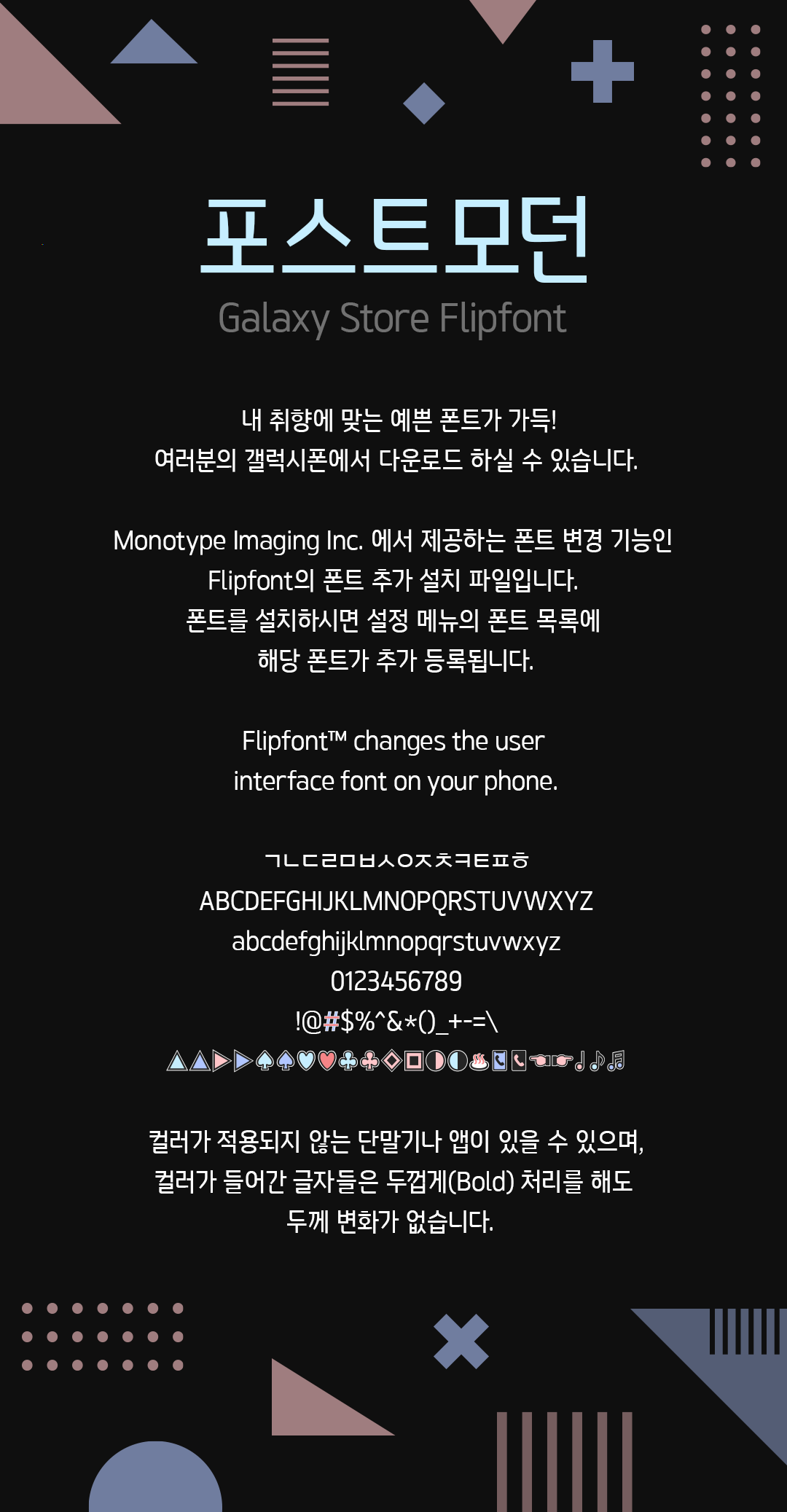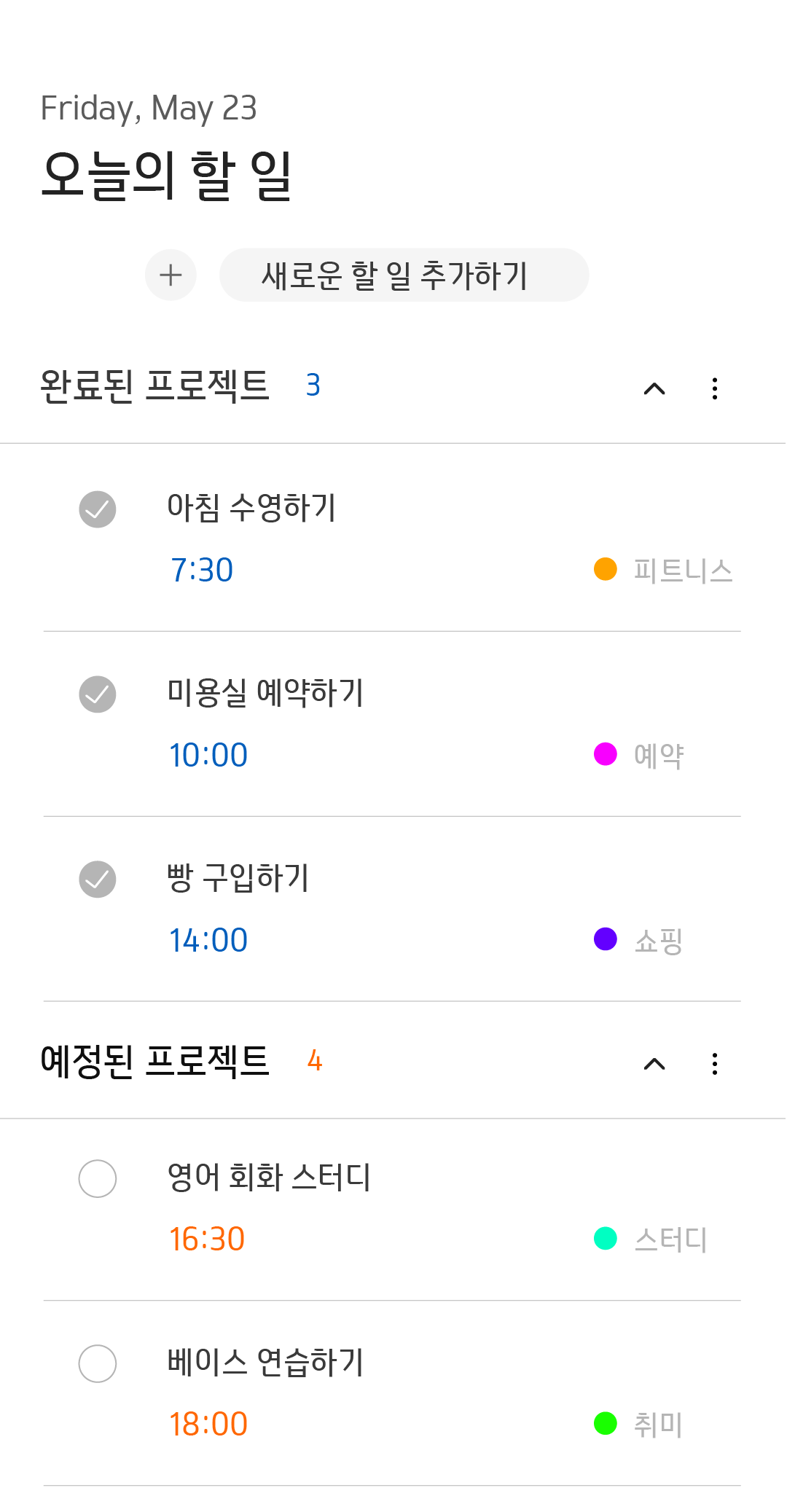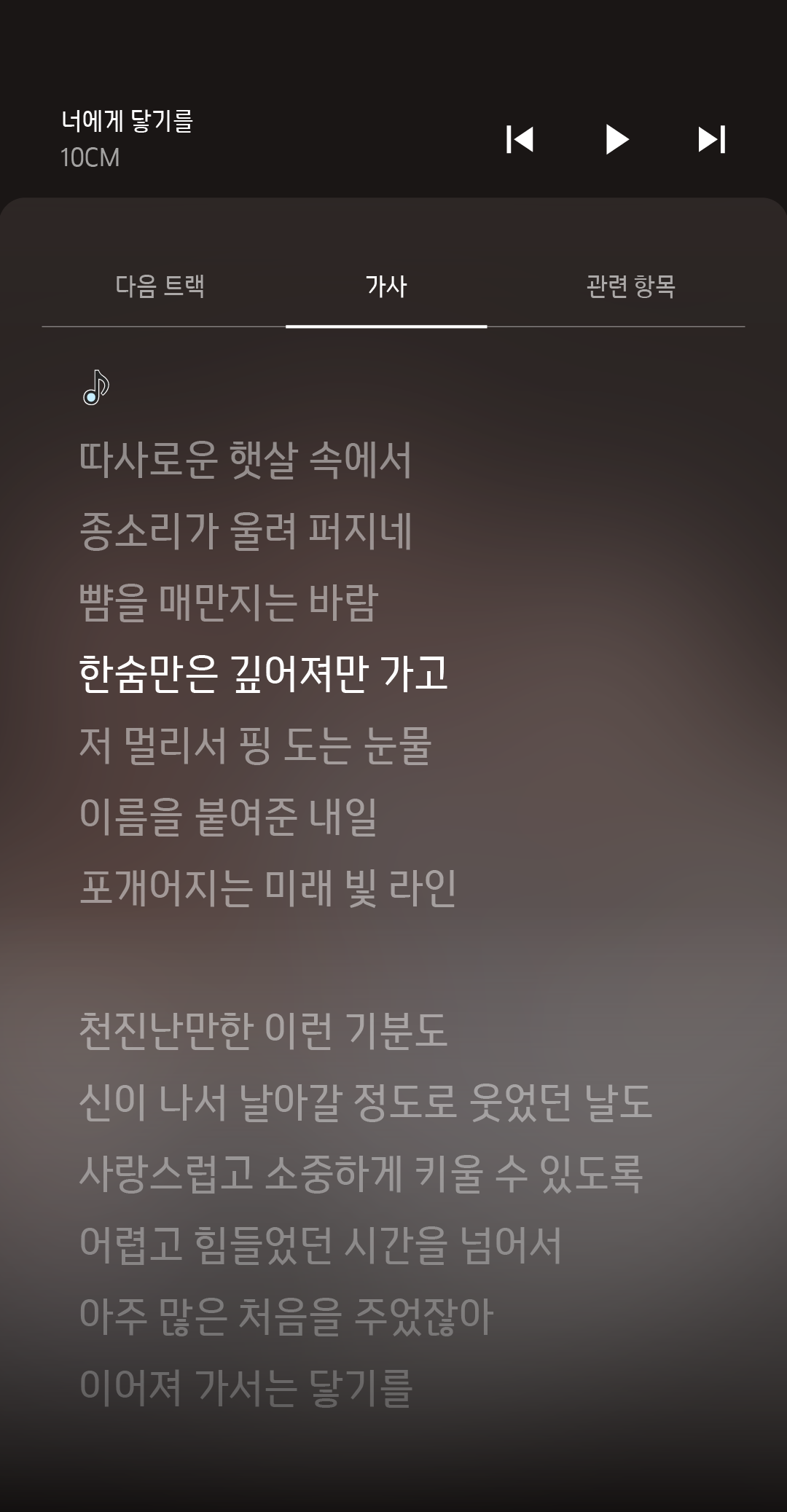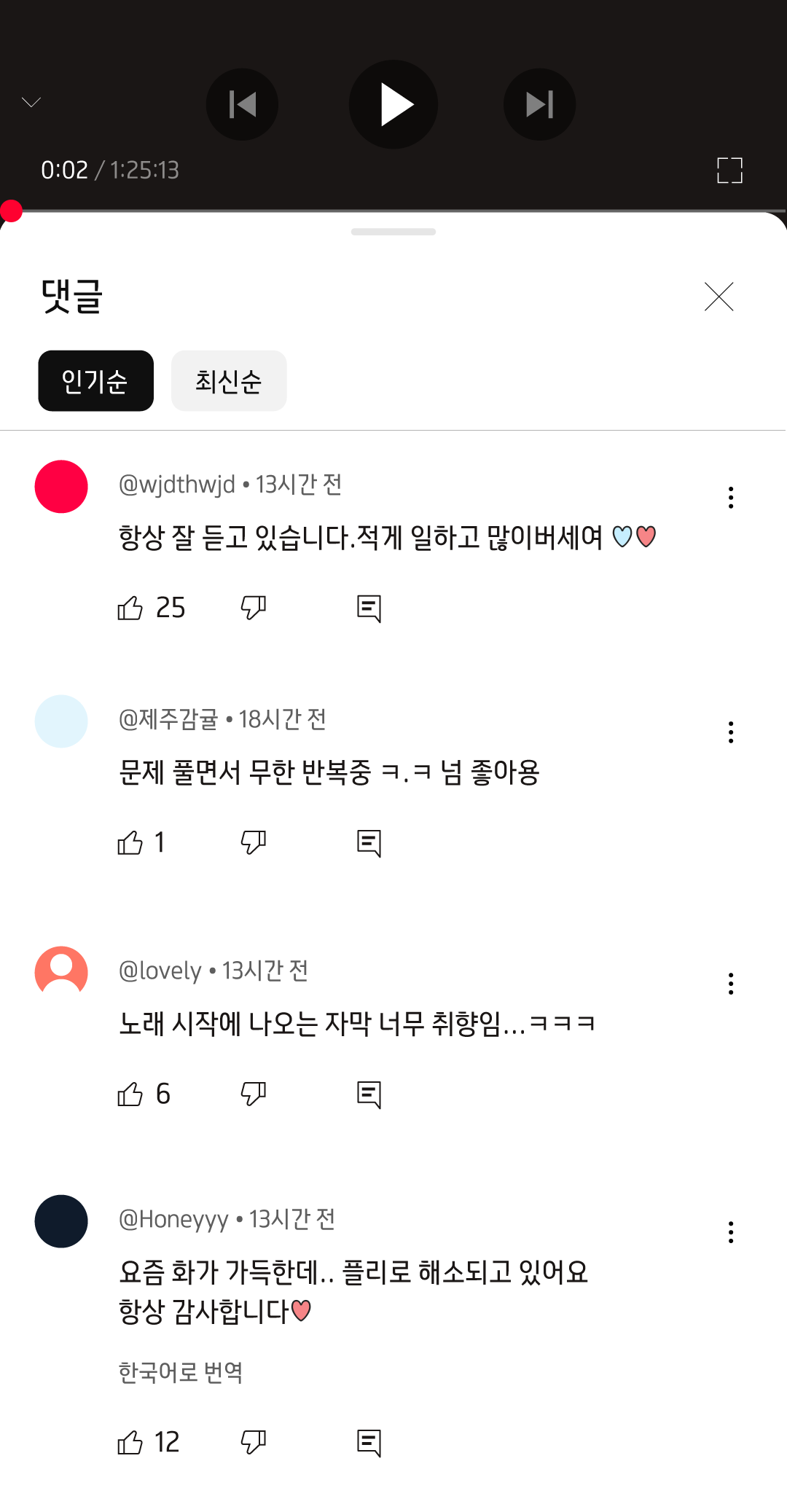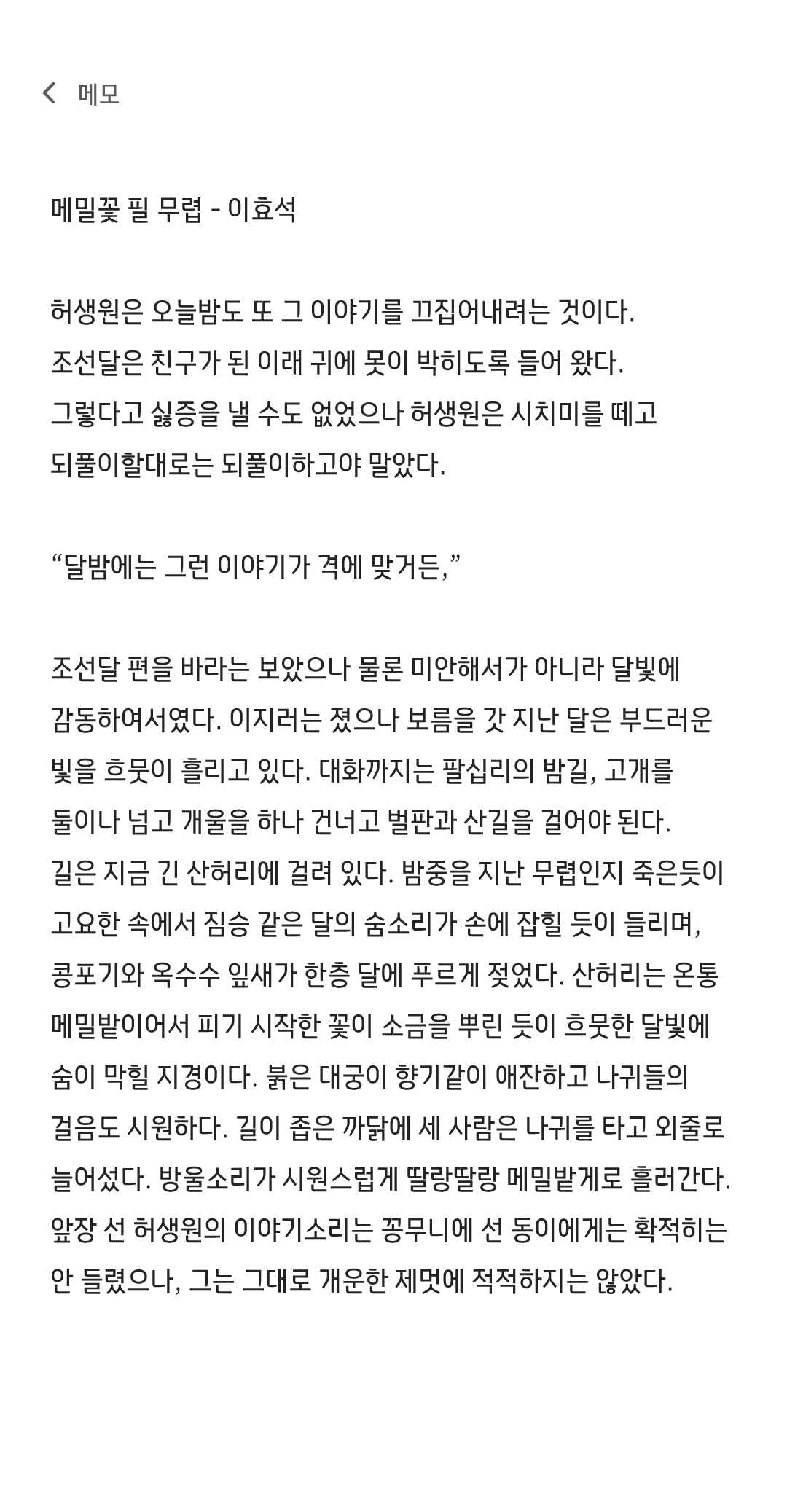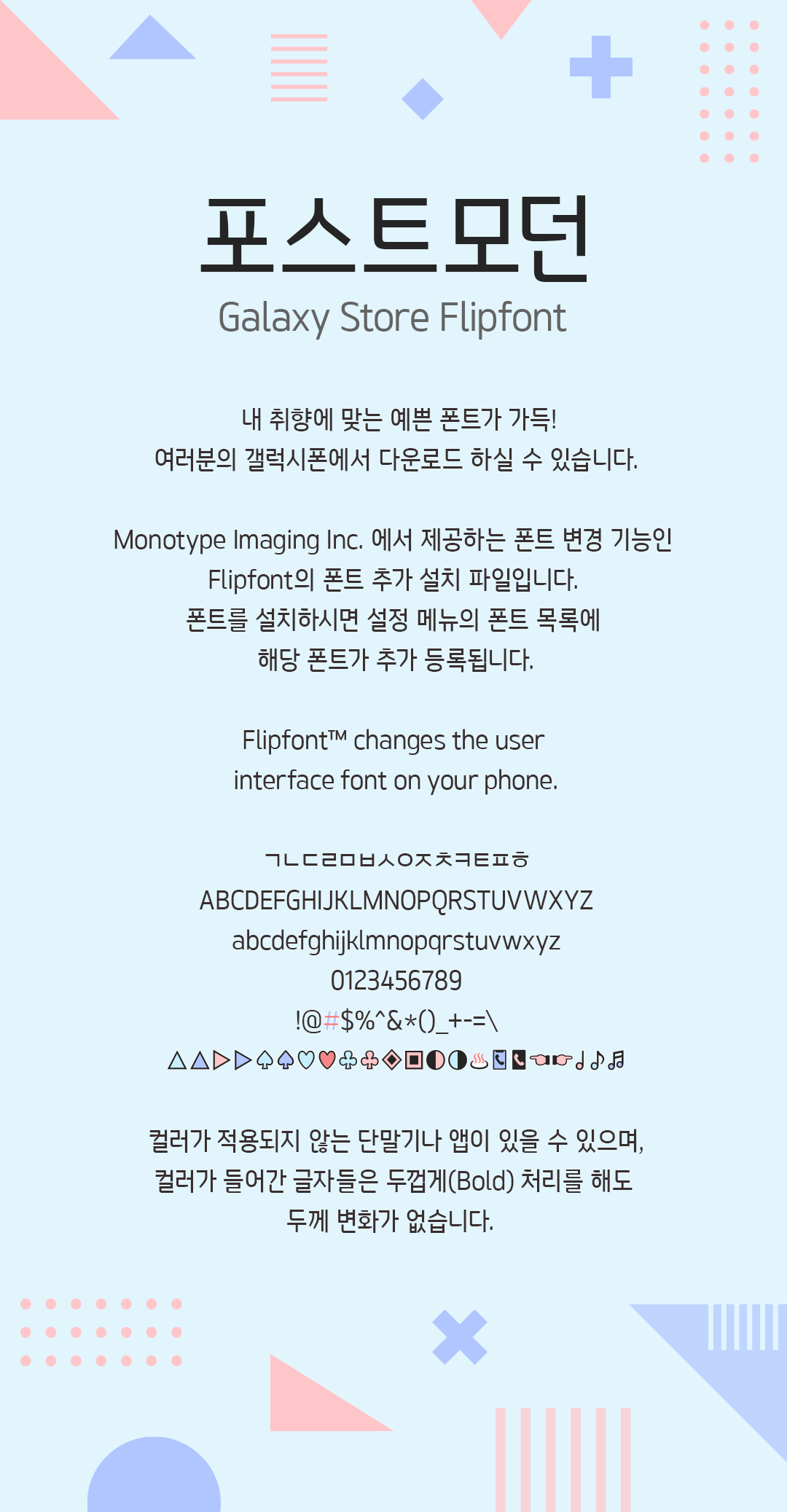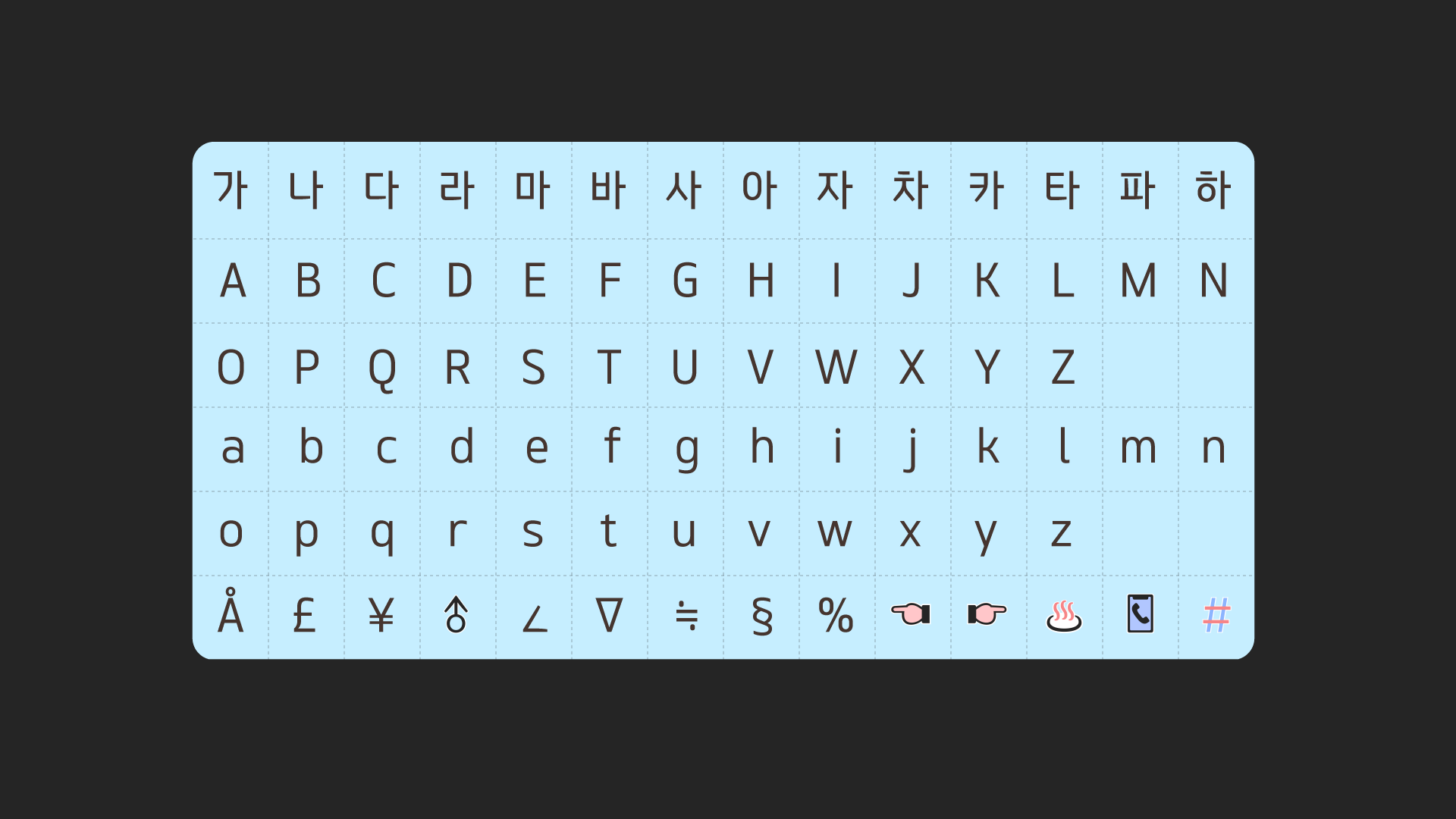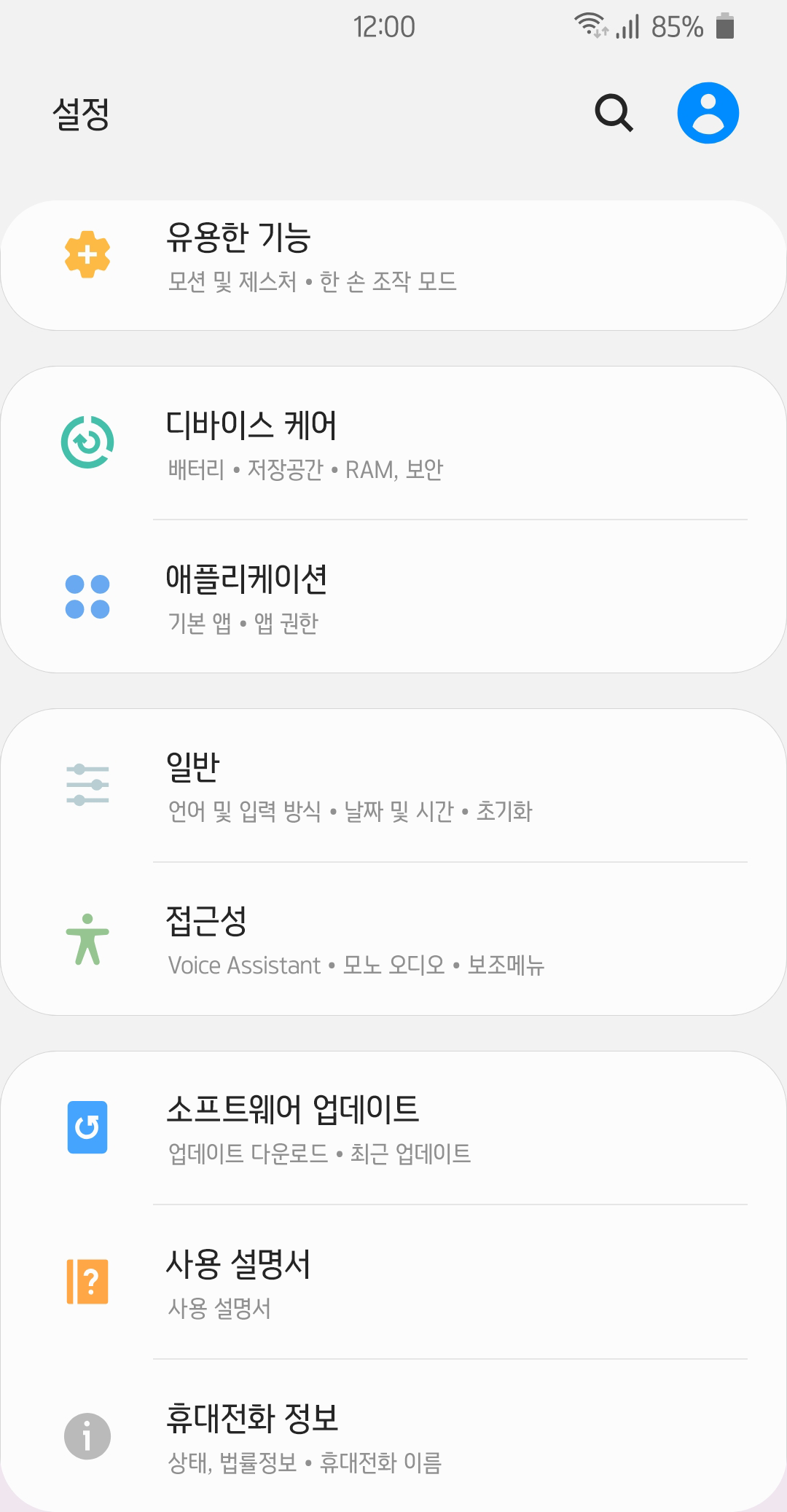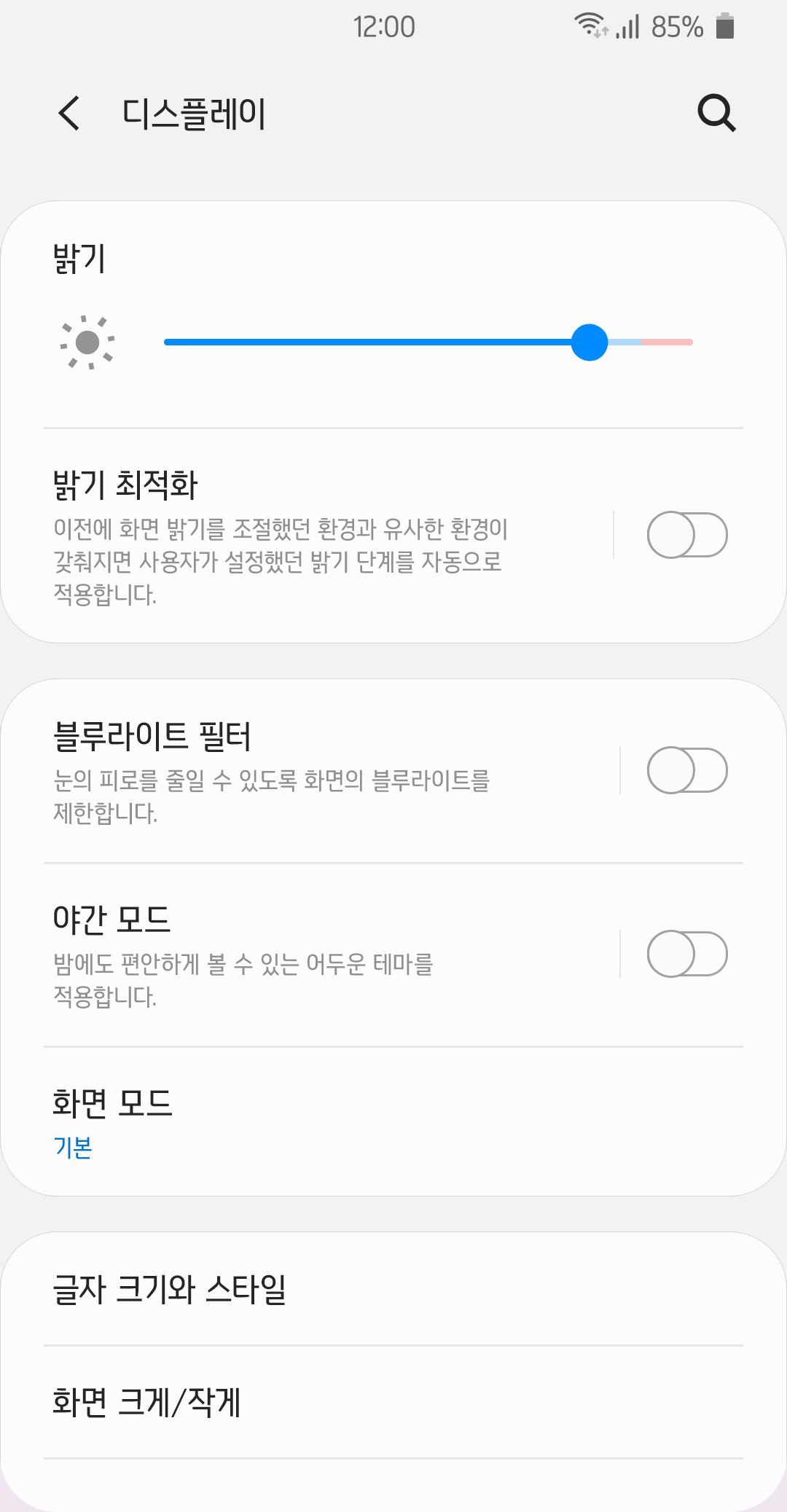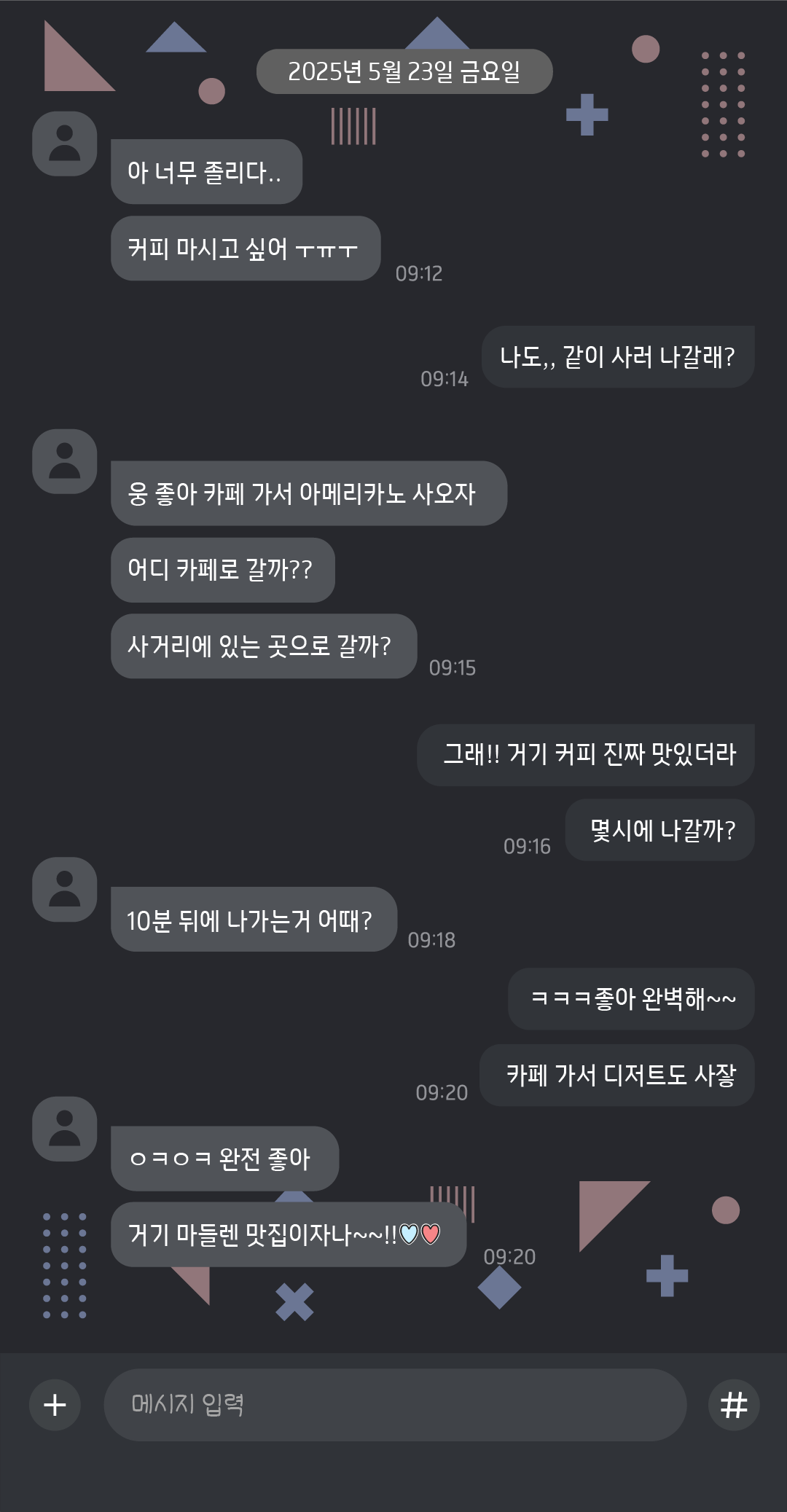
이 서체는 미래지향적인 네오 모던 산세리프 서체로, 명확성, 단순함, 높은 가독성을 강조합니다. 기하학적인 형태로 디자인되었으며, 장식적인 요소는 배제해 깔끔하고 미니멀한 미감을 전달합니다.
이 서체는 미래지향적인 네오 모던 산세리프 서체로, 명확성, 단순함, 높은 가독성을 강조합니다.
기하학적인 형태로 디자인되었으며, 장식적인 요소는 배제해 깔끔하고 미니멀한 미감을 전달합니다.
TE 포스트모던